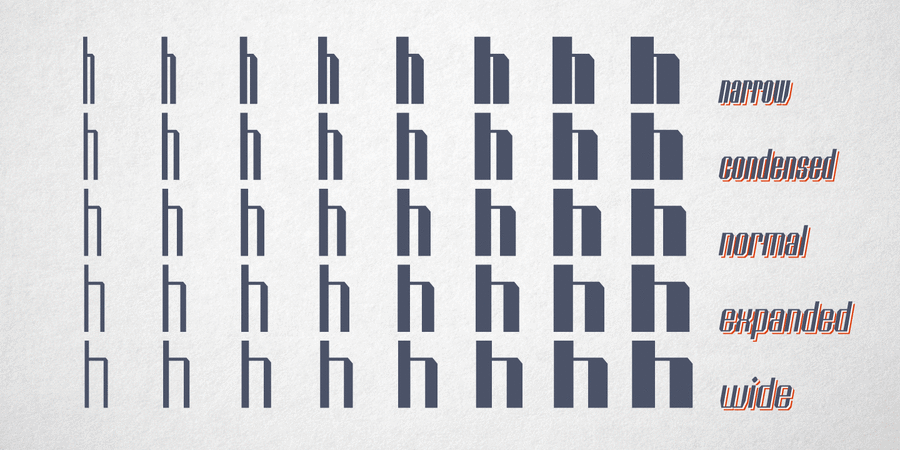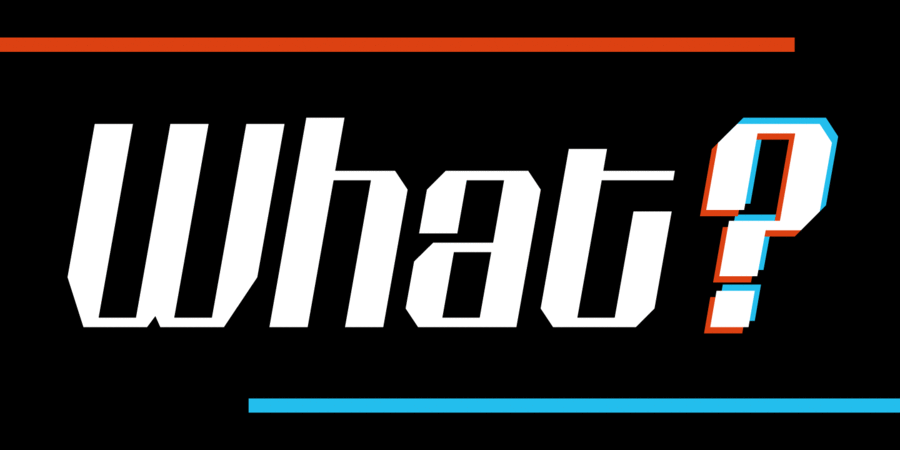
Штозер – це акцидентний шрифт у стилі ретро, створений за мотивами 1960-х і 1970-х років, додатково натхненний кириличної в'яззю. Він поставляється у 8 насиченостях, з 5 варіантами ширини для кожної, все супроводжуються відповідними нахиленими версіями – в цілому 80 накреслень. Shtozer – шрифтове сімейство з широким мовним охопленням, що включає кирилицю. Гарнітура також містить безліч функцій OpenType і альтернативних ґліфів для пожвавлення набору. Шрифт розробив Олег Ліщук у 2020 році.